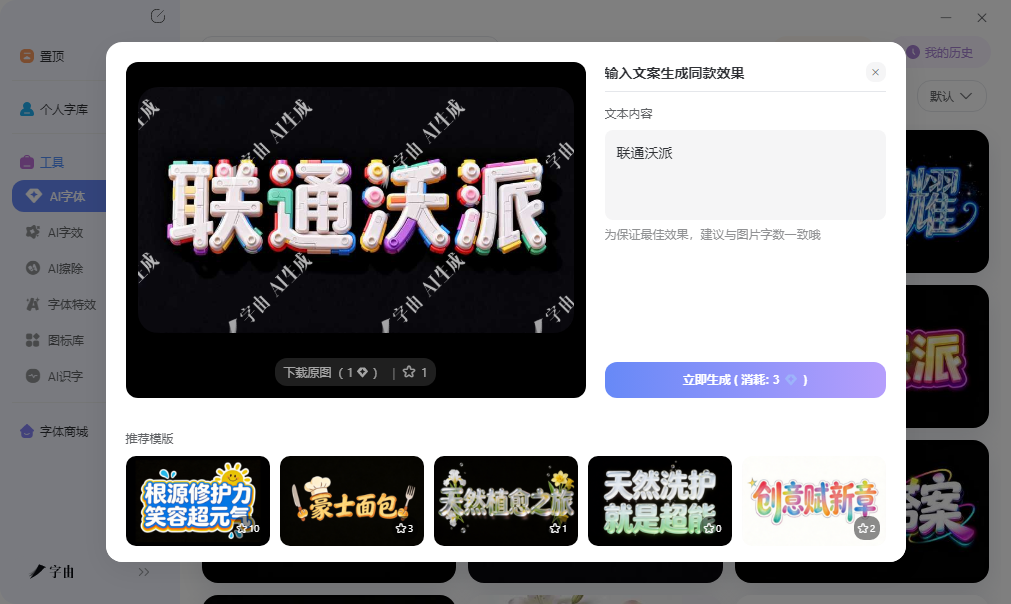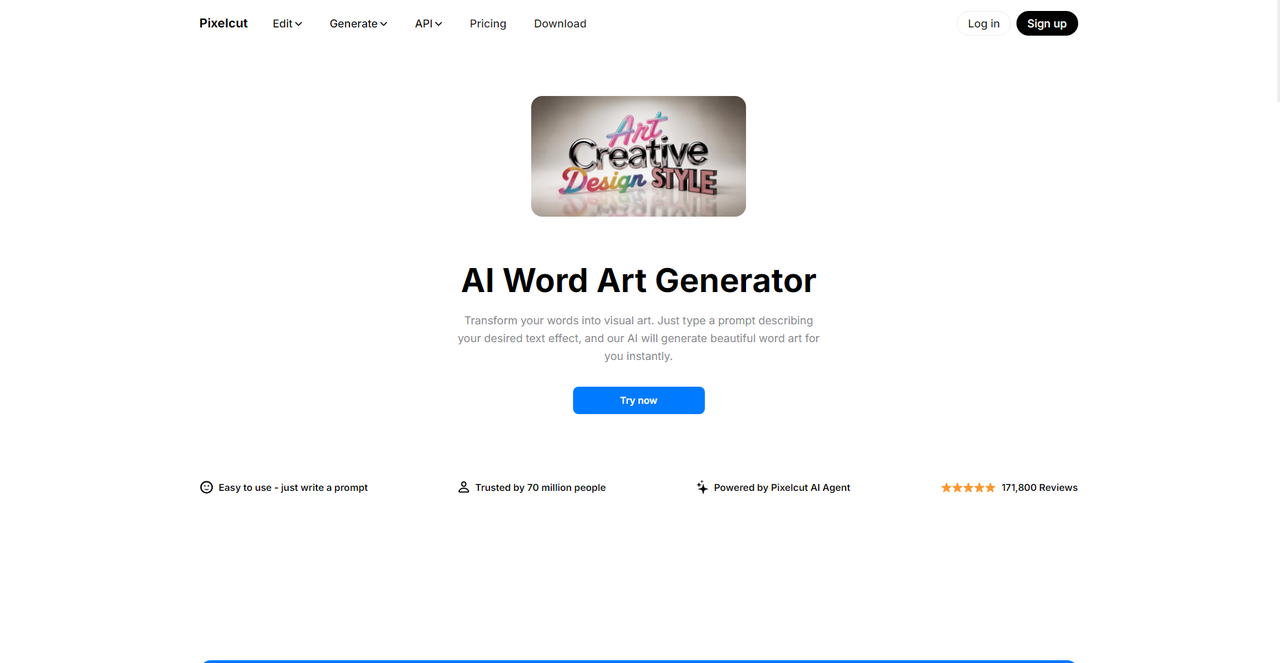
文字特效免费转换器,在线生成艺术字图片
做海报标题或社交媒体封面时,普通字体不够醒目,需要给文字加上发光、立体、金属等特效。不用打开Photoshop慢慢调参数,现在有很多在线工具输入文字就能直接生成艺术字图片。这篇文章测试了5款免费艺术字转换器,有的选模板直接替换文案,有的写提示词让AI生成,有的支持调整分辨率和输出格式。操作难度和生成效果各有不同,按自己的需求选用就行。
字由的AI字体功能是目前操作门槛最低的艺术字生成方式之一。用户不需要学习任何设计软件,也不需要理解发光、阴影、渐变等参数的含义。具体操作步骤如下:
打开字由客户端,进入AI工具下的AI字体页面。左侧标签栏按风格和场景分类,包括国潮风、霓虹灯、金属质感、手写书法、电商促销等。每个分类下都有几十款预制的文字特效模板。这些模板的字体、排版、特效参数都已经由专业设计师调校完成。
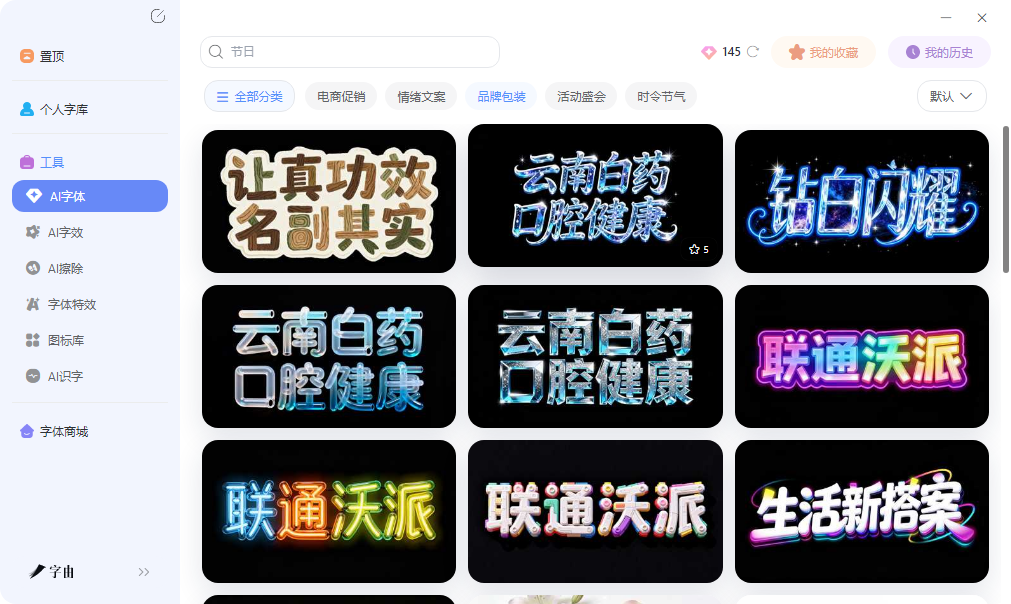
用户选择一个分类,浏览该分类下的模板。每个模板有预览图,鼠标悬停时预览图会显示用户输入的文字效果。用户输入自己的文案后,选择一个模板,点击生成按钮。系统在10到15秒内输出一张PNG格式的图片。图片背景透明,可以直接放在海报或封面中使用。
2、Pixelcut AI Word Art Generator
第二个工具是Pixelcut旗下的AI Word Art Generator。它的操作方式和字由完全不同:用户不需要选模板,而是用文字描述想要的效果,AI根据描述生成艺术字。
用户打开网页,在输入框中输入一段提示词,例如“霓虹灯风格的发光文字,蓝色和紫色渐变,背景黑色”。AI根据这段描述生成对应的文字效果图片。平台宣称由Pixelcut AI Agent驱动,已累计服务7000万用户。适用场景:当用户有明确的效果想法但找不到现成模板时,可以通过写提示词让AI直接生成。例如用户想要一个蒸汽波风格、带故障特效、粉紫色调的文字,用关键词描述后AI会尝试生成接近的效果。缺点是AI生成的结果可能存在不稳定性,同一个提示词不同时间生成的结果可能有差异。
3、Fonts Generator
第三个网站是Fonts Generator。它的Text Art Font Generator板块专注于复古风格和装饰性文字效果。用户在上方输入文字,下方实时展示多种文字效果。效果类型包括Text Art(文字艺术)、SquaredLetters(方块字母)、Retovibes(复古氛围)等。每种效果以预览图形式展示,用户点击喜欢的样式后可以一键复制,或下载图片。该工具生成的文字效果以图片形式输出,适合用于社交媒体配图、个人网站Banner、复古风格海报等。完全免费,无需注册,界面简洁。
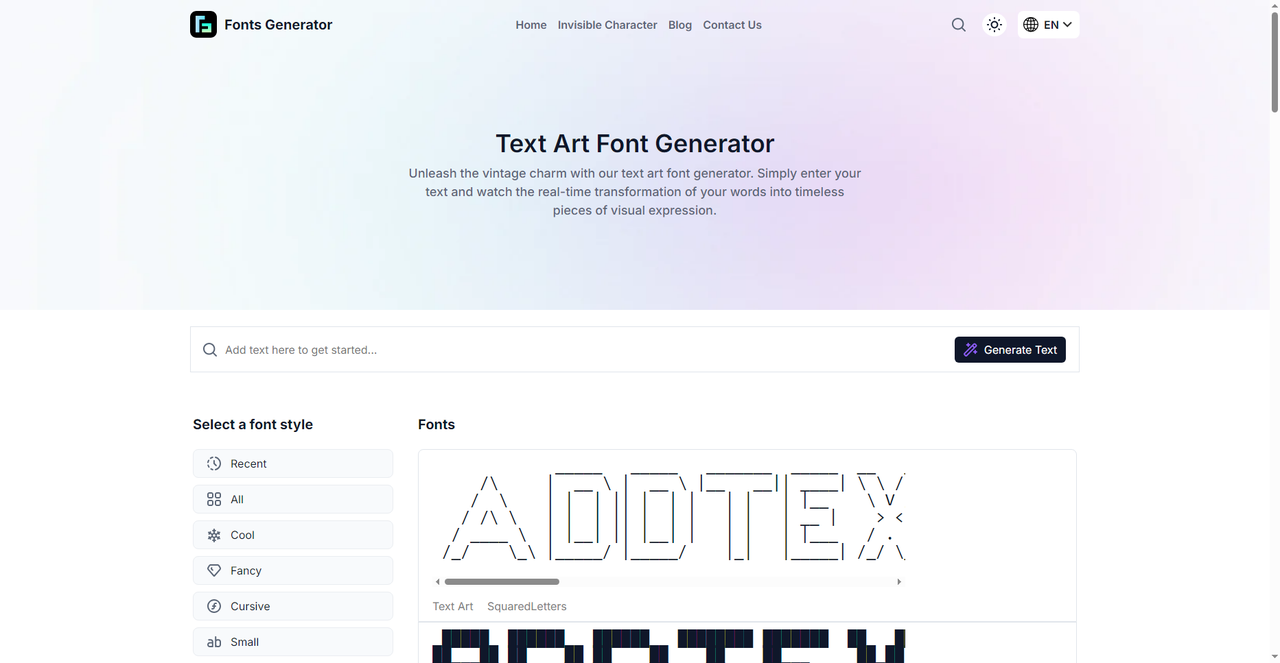
4、Text Effects
第四个平台是Text Effects。它的核心功能是将普通文字转换成带有特定效果的艺术字。用户在上方输入框输入文字,在下方输入想要的特效描述(例如“3D立体、金属质感、红色渐变”),系统生成对应的文字效果图片:Text Effects更偏向于特效关键词匹配,用户不需要写完整的描述句子,输入几个关键词(如霓虹、阴影、描边)即可。生成速度较快,适合想要快速尝试几种不同特效的用户。平台还提供了热门特效推荐,用户可以一键套用。生成结果可以下载为图片,支持常见的JPG和PNG格式。免费使用,无需注册。
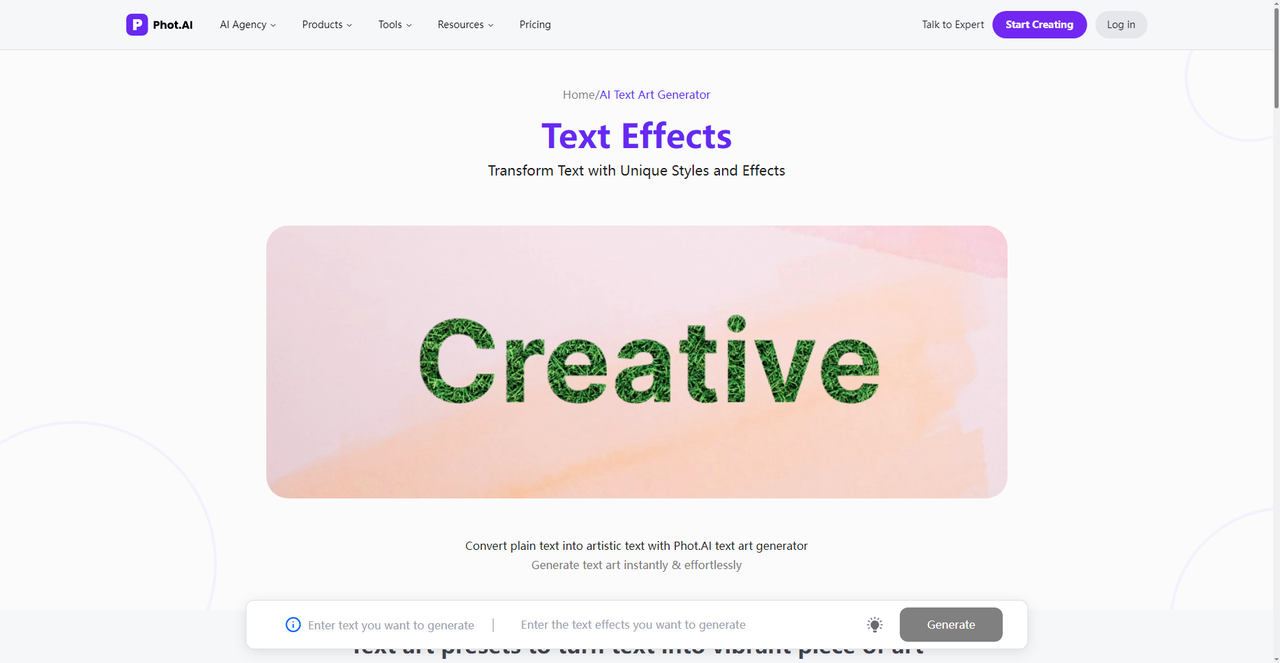
5、AI WordArt Generator
第五个工具是AI WordArt Generator。它的参数调节选项比前面几个更丰富。用户输入要转换的文字,选择整体风格(例如3D、背景、立体等),设置输出长宽比(支持21:9、16:9、3:2、4:3、1:1、3:4、9:16等多种比例),以及输出分辨率(1K、2K、4K可选)。分辨率越高,图片细节越丰富,适合印刷或高清屏幕展示。当用户对输出图片的尺寸和清晰度有明确要求时,例如需要制作印刷级海报或4K视频封面,这个工具的分辨率调节功能很有用。高分辨率生成需要更多时间,免费版可能有次数限制。网站还集成了其他AI工具,如文字转图像、AI音乐生成、AI故事生成等,用户可以在同一平台上完成多种创作任务。对于需要批量处理文字特效的用户,可以考虑收藏。